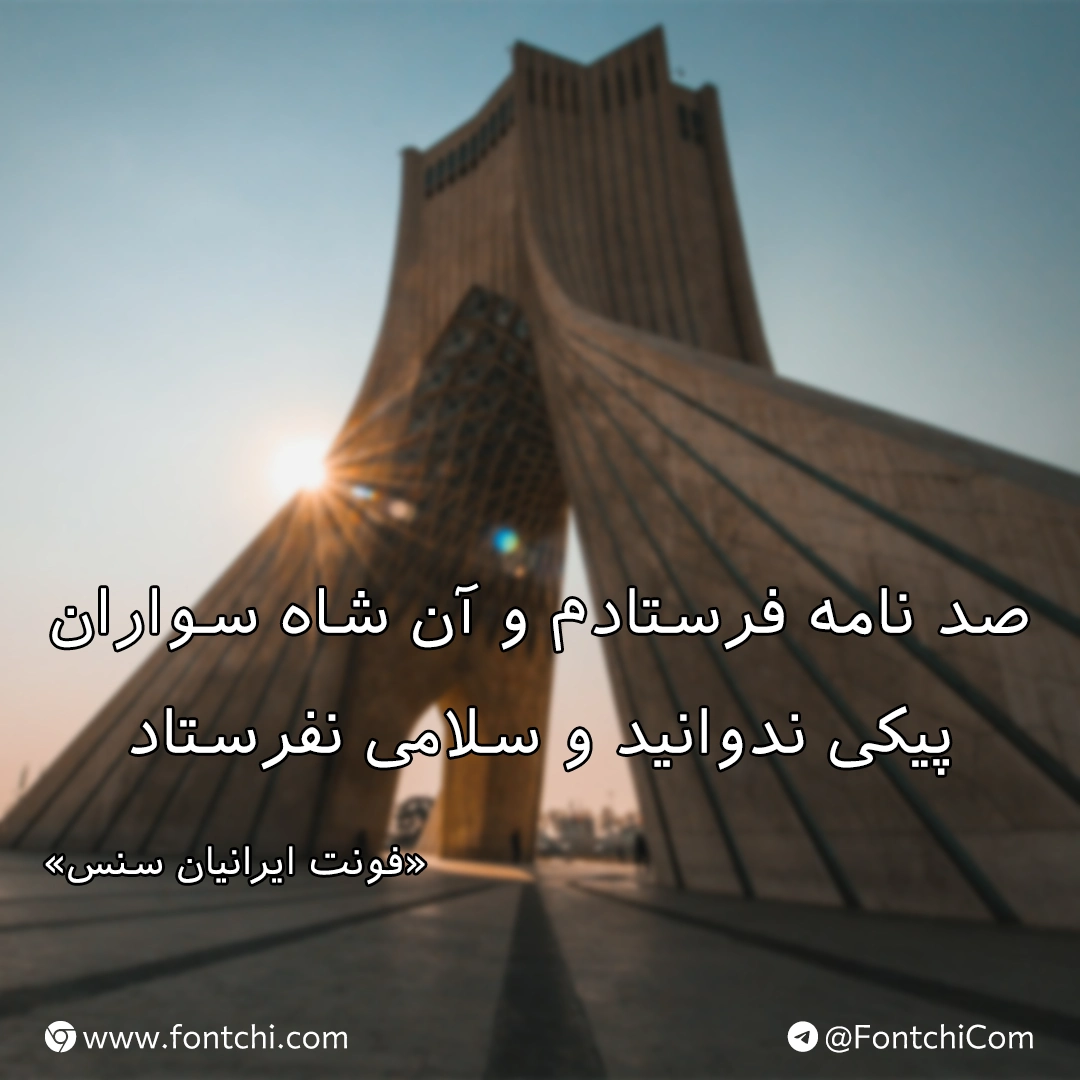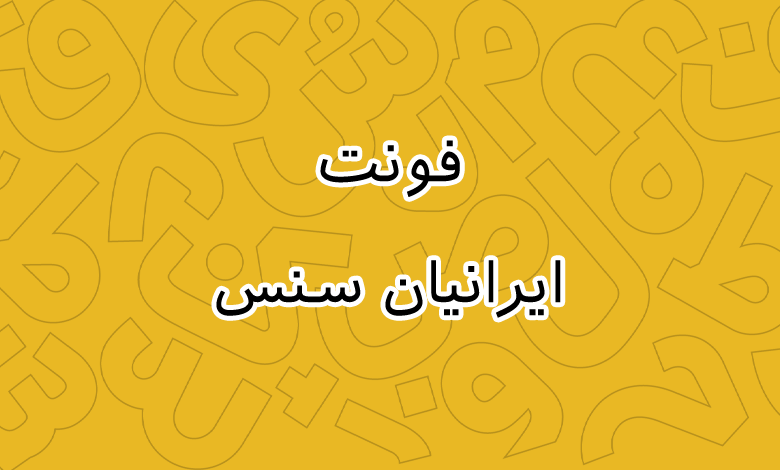
فونت ایرانیان سنس (Iranian sans)
| نام | ایرانیان سنس |
| نام نمایشی | Iranian sans |
| طراح | هومن مهر |
فونت ایرانیان سنس (به انگلیسی: Iranian sans) جزو اولین قلمهای آزاد فارسی است که سبک جدیدی از طراحی را بهخود گرفته و الگوی ساخت بسیاری از فونتهای پرمیوم امروزی است. این فونت فارسی در سبک سنس طراحی شده است که در ادامه با دانلود رایگان فونت ایرانیان سنس با شما همراه هستیم.
طراحی فونت ایرانیان سنس توسط هومن مهر انجام گرفته است. این فونت صرفا دارای یک وزن معمولی Regular است که میتوانید از آن در پروژهها و محیطهایی که نیاز به فونتی با خوانایی بالا در متون بلند دارید استفاده کنید. در تصویر زیر پیشنمایش این فونت را مشاهده کنید.
فونت فارسی ایرانیان سنس از زبان عربی نیز پشتیبانی میکند و در لیست گلیفهای این فونت اعداد فارسی به شکل استاندارد طراحی شده است. همچنین این فونت با زبان عربی سازگاری دارد که علاوه بر گلیفهای متفاوت حروف عربی، اعراب و اعداد «٠٤٥٦» دارای گلیف استاندارد خود هستند.
قلم ایرانیان سنس دارای یک وزن معمولی است که حروف در آن به شکل سنس طراحی شدهاند. اما میتوان تا حدودی ظاهری هندسی و نزدیک به خط نسخ را نیز در این قلم دید. چشمیها در برخی حروف بزرگتر هستند، منحنیها با ترکیبی از دایره و مربع ادغام شدهاند و دندانهها نیز برای نمایشیتر کردن فونت، در برخی حروف مثل «س، ش» به شکل مورب هستند.
از این فونت میتوانید در پروژهها و محیطهایی که متون طولانی دارید استفاده کنید. از صنعت مطبوعات برای چاپ روزنامه، مجله و کتاب گرفته تا صفحات وب و اپلیکیشن موبایل که میتواند انتخاب خوبی باشد.